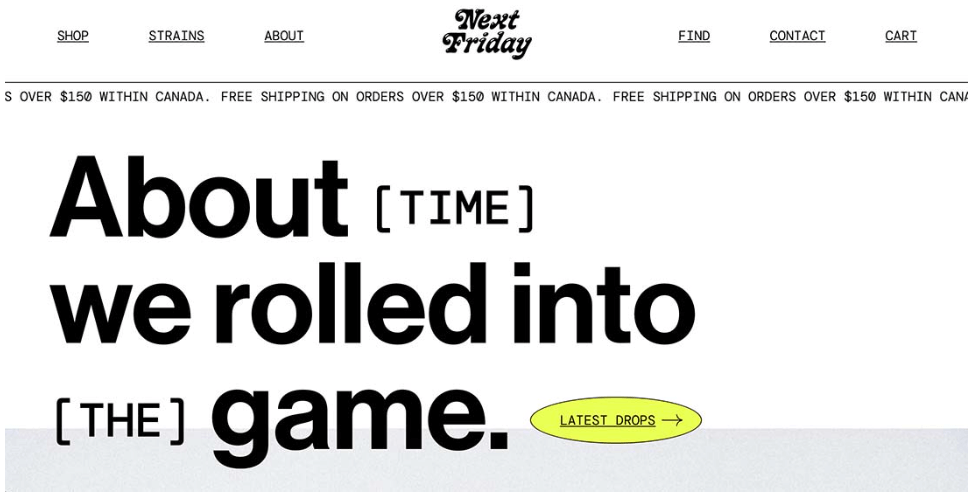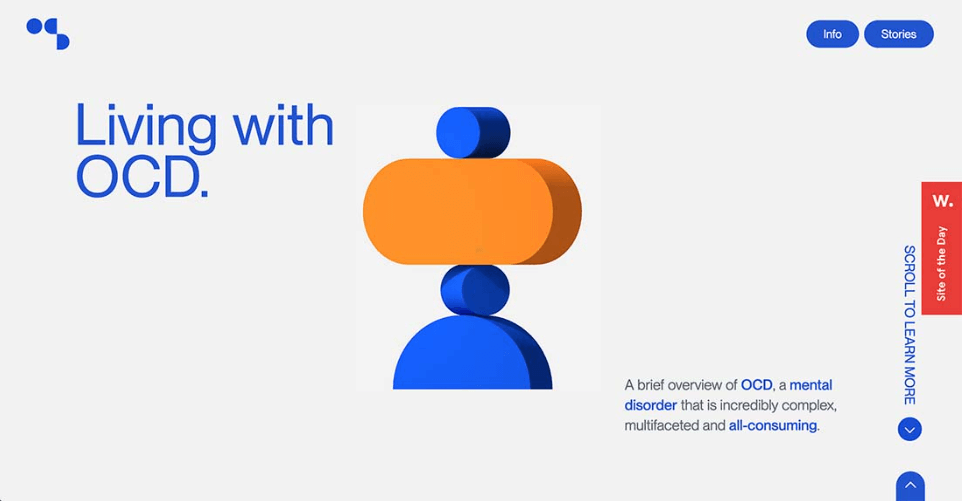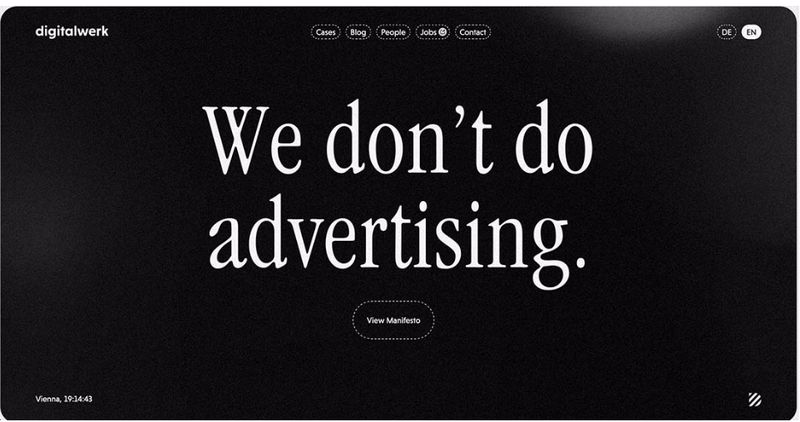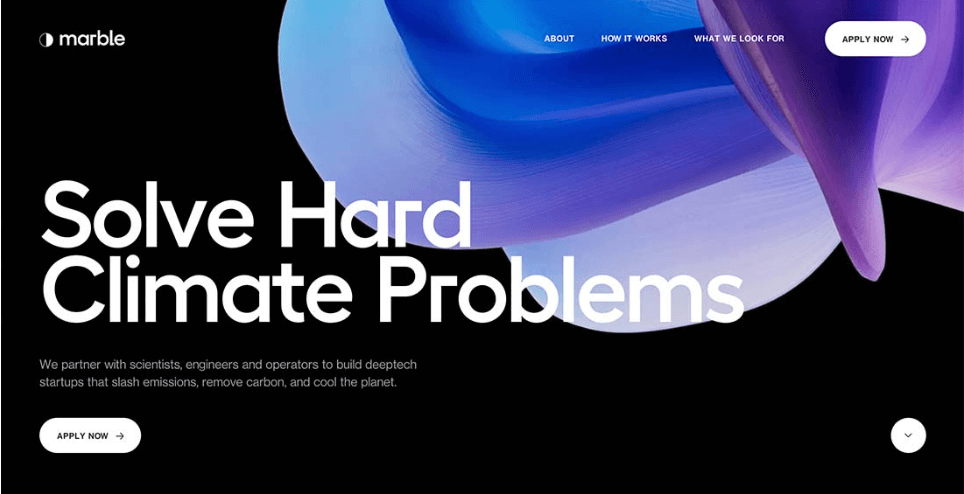
Один из самых важных вопросов, который может возникнуть у вас в процессе создания веб-сайта — какой шрифт лучше всего подходит моему проекту?
При выборе шрифта важно думать о содержании, контексте и целевой аудитории, а также не забывать о тестировании шрифта с помощью пользователей.
В этой статье мы расскажем вам о том, как правильно выбрать красивый и легко читаемый шрифт для веб-сайта, а также поделимся примерами для вашего вдохновения.
Есть несколько шрифтов, которые можно назвать идеальными с точки зрения читаемости. В основном к ним относятся простые шрифты без засечек.
Компания Adobe провела исследование, в котором обнаружила, что выбор шрифта и его читабельность зависят от скорости чтения. Поэтому при выборе шрифтов ориентируйтесь на потребности вашей целевой аудитории. Ниже мы рассмотрим несколько рекомендаций:
Большое значение имеет размер, интервалы и общий масштаб шрифтов относительно вашего проекта. Все эти параметры очень влияют на удобство чтения.
Чем проще визуально отсканировать ваш текст, тем более удобным и понятным он будет — это особенно важно для молодых пользователей, у которых более низкая концентрация внимания.
Еще один важный фактор, который способствует удобочитаемости — это скорость загрузки шрифтов на веб-сайте. Поэтому мы рекомендуем использовать простые и понятные шрифты из библиотеки Google, которые не очень тяжелые, но в то же время стильные и привлекательные.
Не стоит использовать пользовательские варианты шрифтов, если в этом нет острой необходимости — обычно такие шрифт много весят и долго загружаются.
Мы советуем использовать шрифт со средней высотой и шириной, а также закругленные, но не слишком сжатые буквы. На первый взгляд это может показаться скучным, но простота и минимализм в — это ключ к успеху.
Хотя цвет фона и контрастность не являются частью шрифта, эти параметры могут сильно повлиять на общий вид вашего дизайн-проекта.
Чтобы обеспечить контрастность и доступность, следуйте рекомендациям W3C по использованию коэффициента контрастности между текстом и фоном — она должна быть не менее 4:5:1.
Эта рекомендация звучит необычно, согласитесь? Но мы действительно советуем вам распечатать ваш дизайн-проект на бумаге, чтобы оценить общую читабельность. Кроме этого вы сможете проверить, насколько ваш шрифт четкий и как он выглядит с дальнего расстояния.
Мнение ваших пользователей поможет вам проанализировать не только ваш дизайн в целом, но и отдельный элементы, например, выбор шрифта.
Особенно это будет полезно, если вы используете новые и экспериментальные шрифты. В идеале запросить отзыв до запуска веб-сайта, но вы можете это сделать уже с работающим сайтом — лучше поздно, чем никогда.